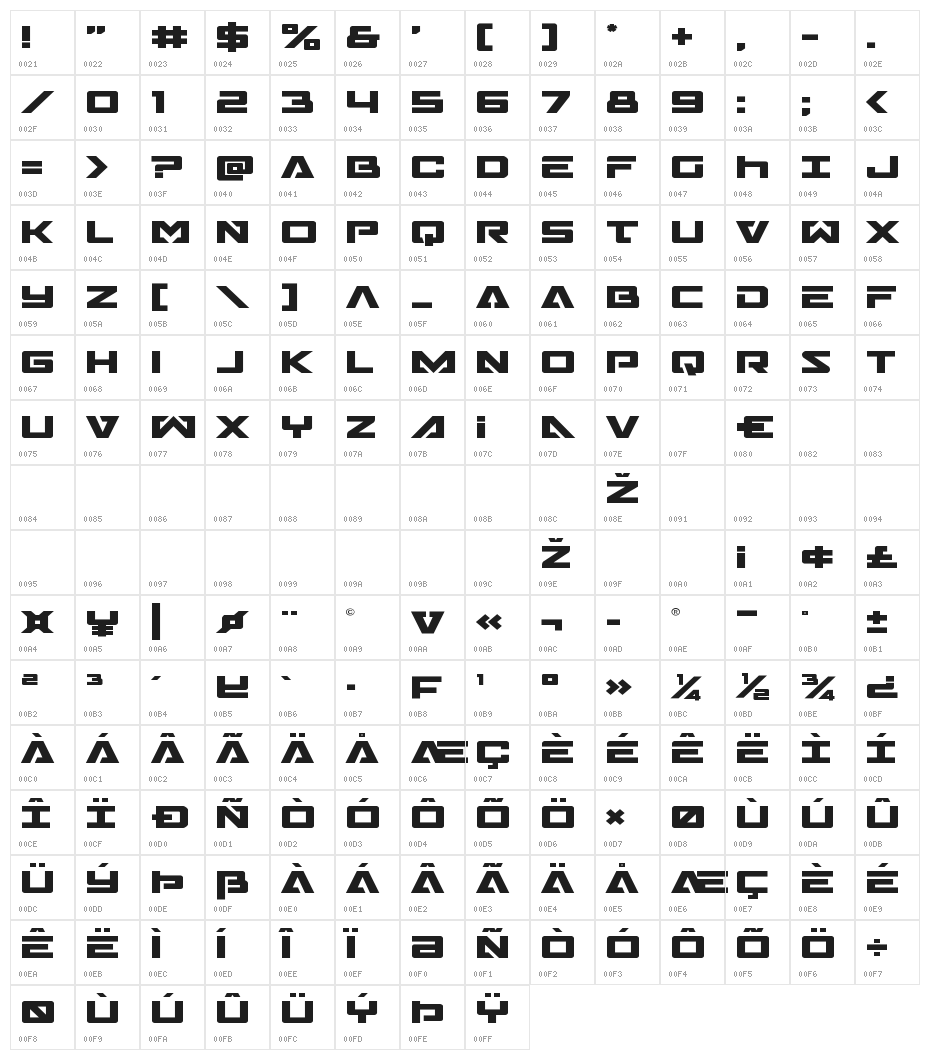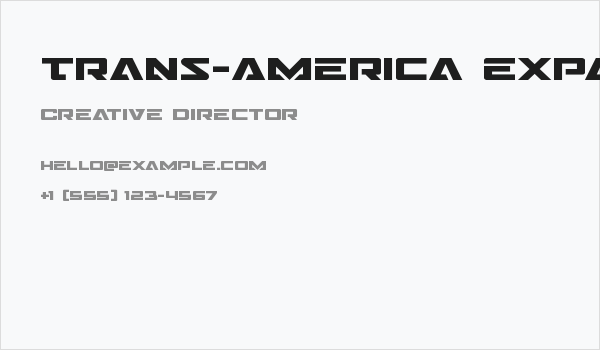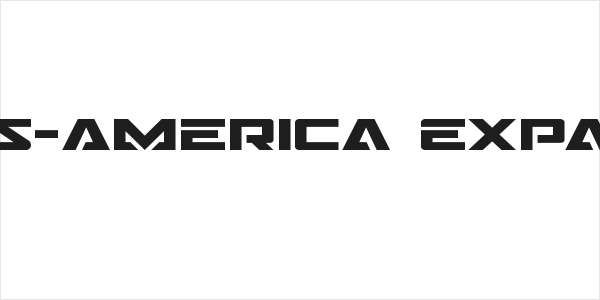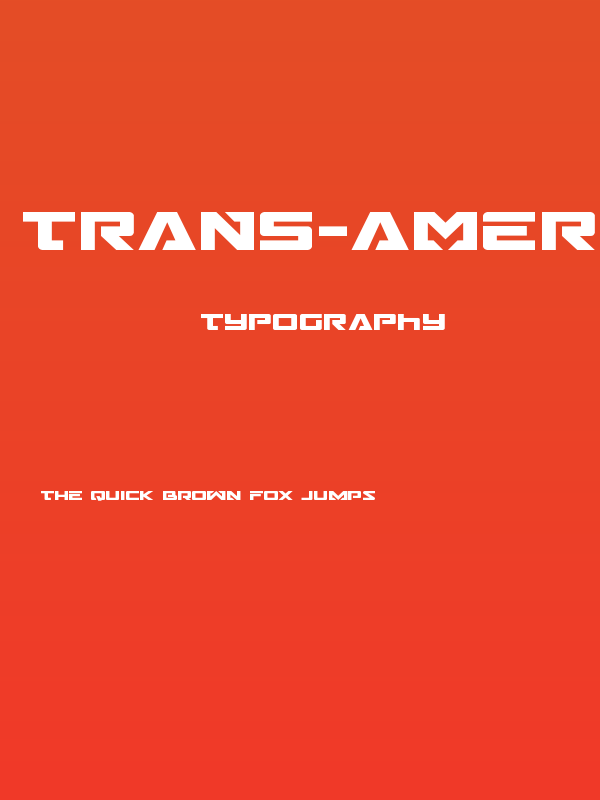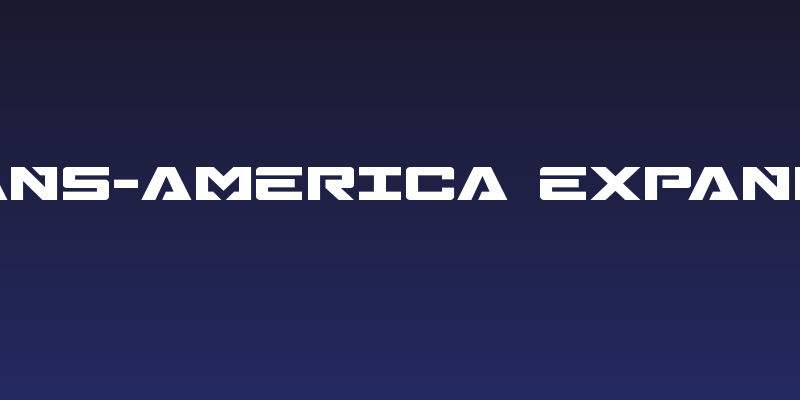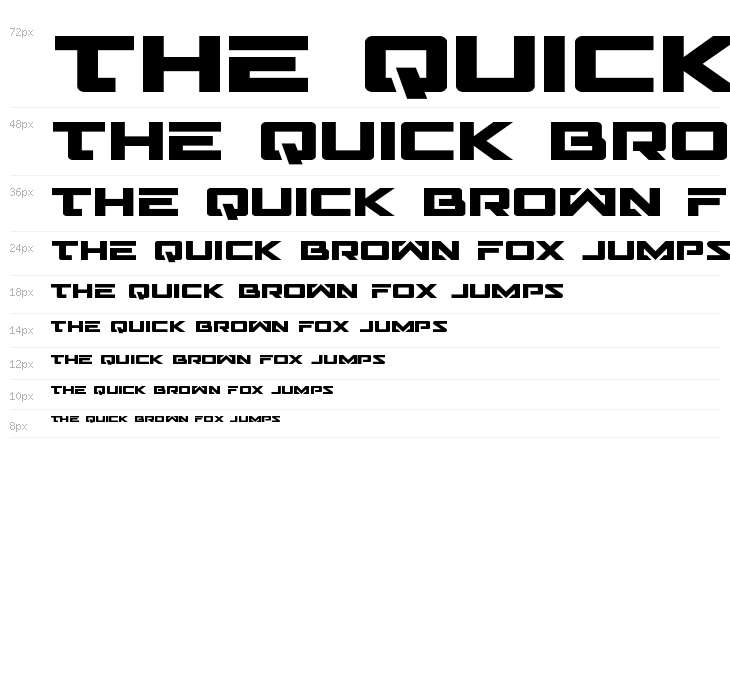
Trans-America Expanded Font
| Peso | Expanded |
| Larghezza | Expanded |
| Progetti proposti | Ideal for branding, posters, and headlines that need a modern, assertive look. |